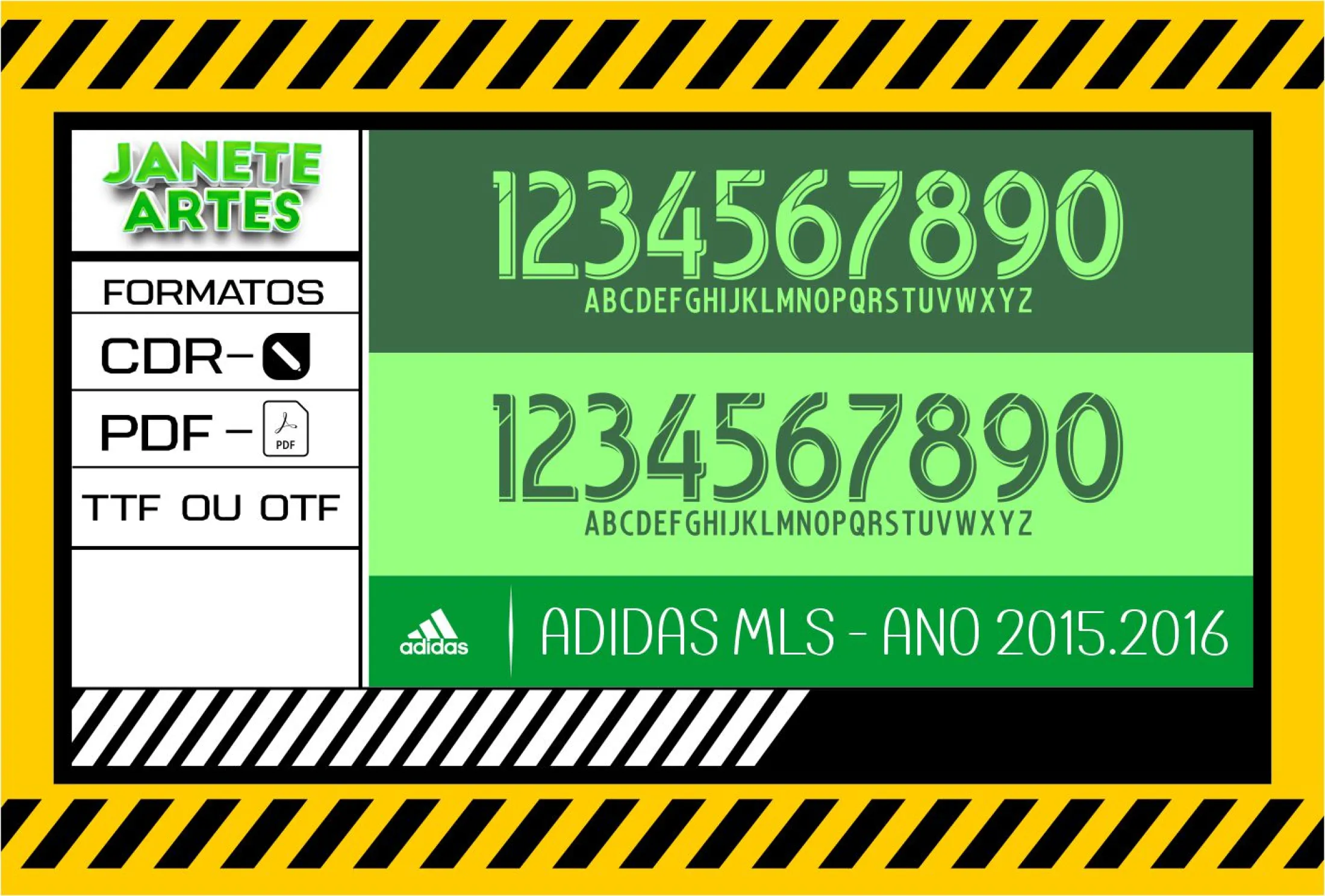
Fonte de Time Tipografia Adidas MLS 2016
Fonte de Time Tipografia Adidas MLS 2016 é um arquivo digital que traz a tipografia exclusiva para personalizar camisetas com design esportivo e moderno, perfeito para fãs e torcedores que querem dar estilo ao visual.
Uma história de paixão e identidade no futebol
Imagine a emoção da torcida vibrando em cada jogo, com a camisa personalizada do seu time favorito, exibindo a clássica fonte Adidas MLS 2016. João, um fã de futebol, sempre quis criar sua própria camiseta para sentir mais perto do clube durante os jogos com os amigos. Ele encontrou no Arte Fonte de Time Tipografia Adidas MLS 2016 para Camiseta a solução perfeita para dar vida ao seu desejo. Na primeira festa do time, todos notaram a originalidade do visual, e João se sentiu ainda mais conectado com a torcida. Essa história pode ser sua também, com um toque único e profissional.
• Fonte exclusiva da tipografia Adidas MLS 2016, perfeita para aplicar em camisetas, camisas e blusas.
Dicas para aplicar e combinar sua personalização
• Combine a tipografia com números ou nomes dos jogadores para camisas temáticas.
Transforme seu projeto com o Arte Fonte de Time Tipografia Adidas MLS 2016 para Camiseta e leve o estilo da tipografia oficial para suas camisetas, camisas e blusas favoritas.